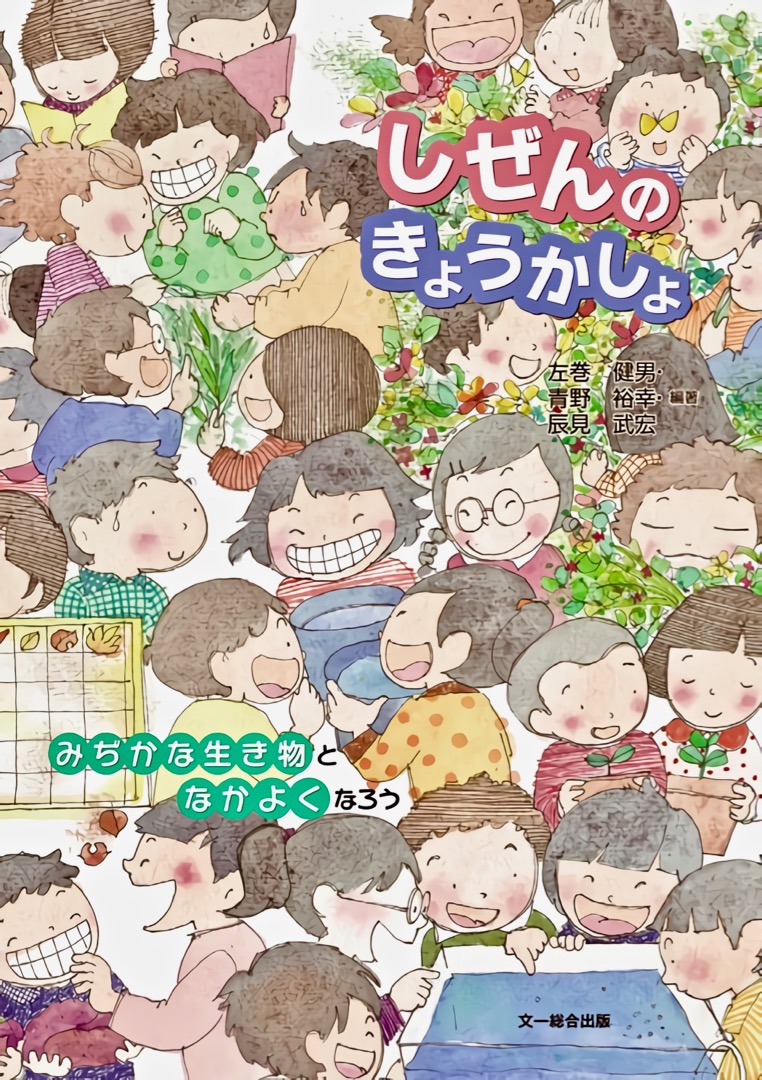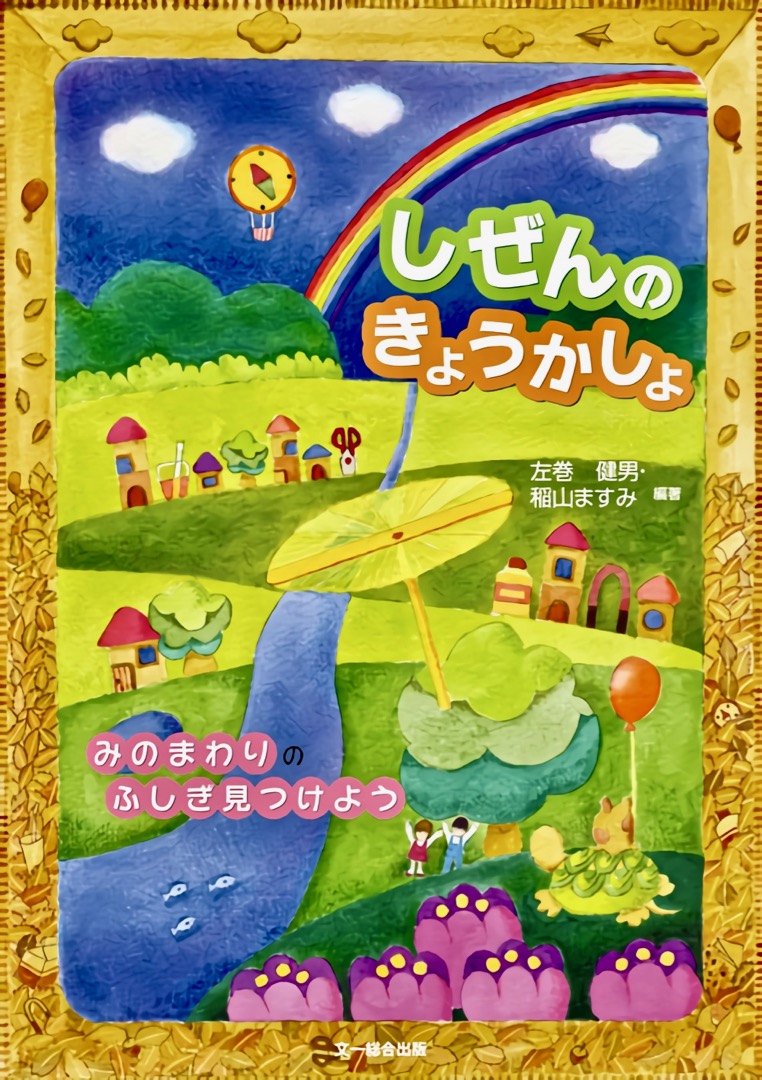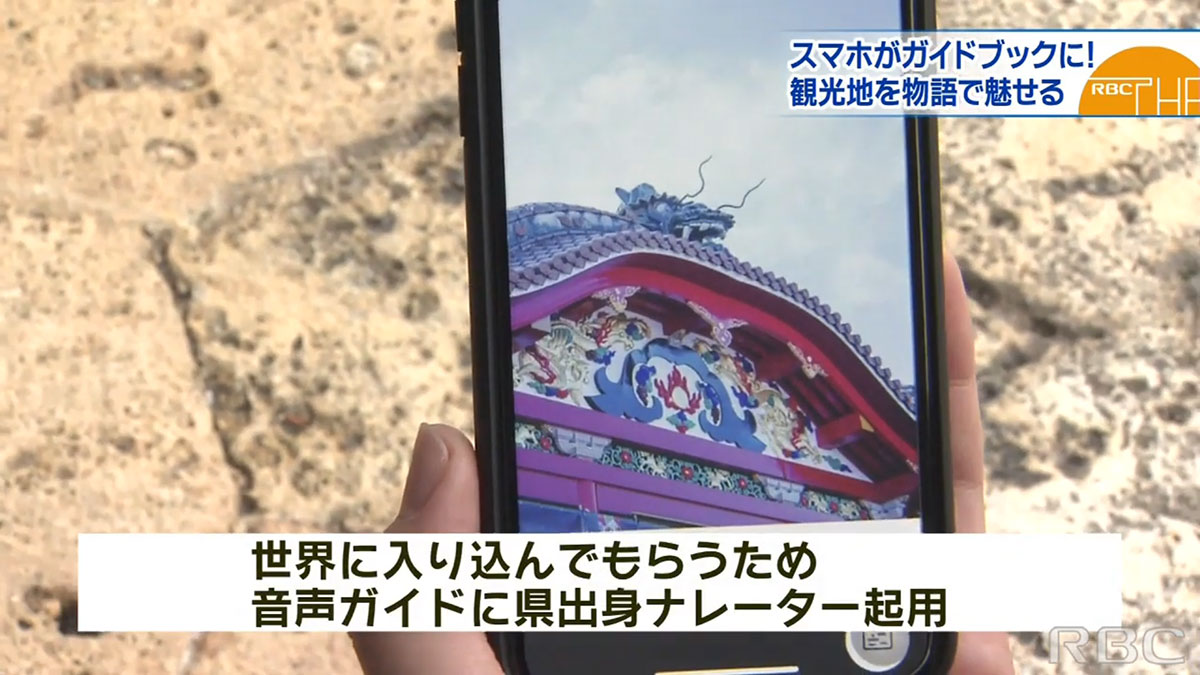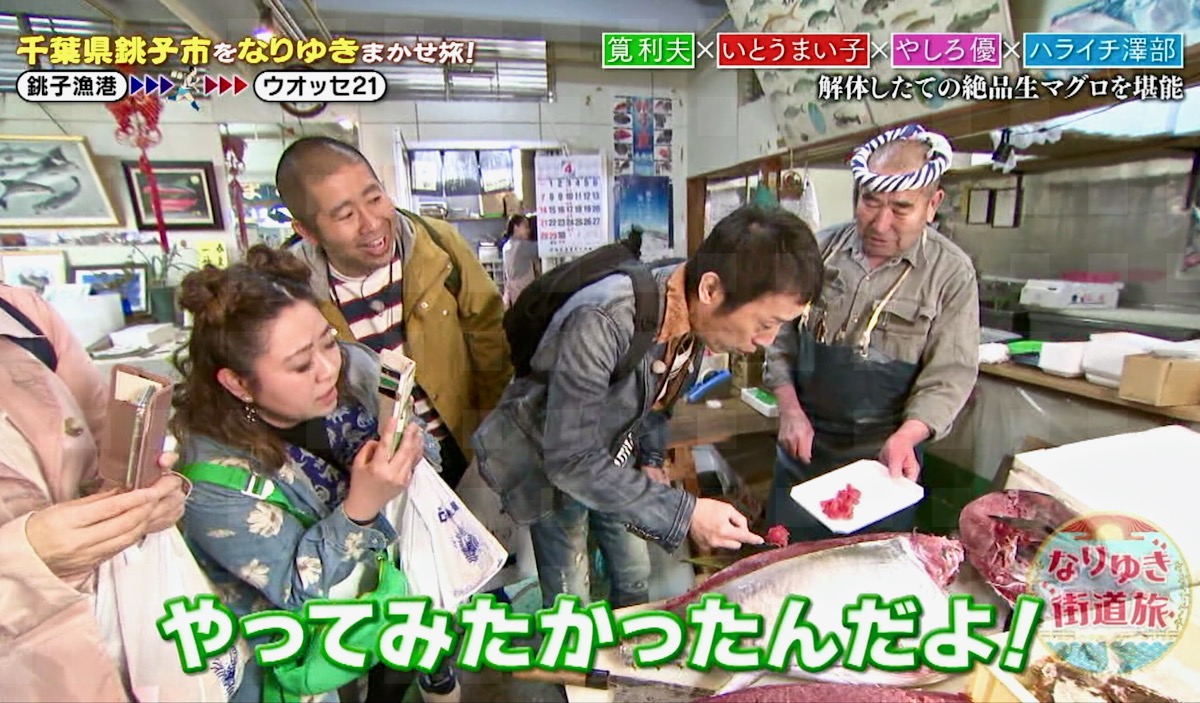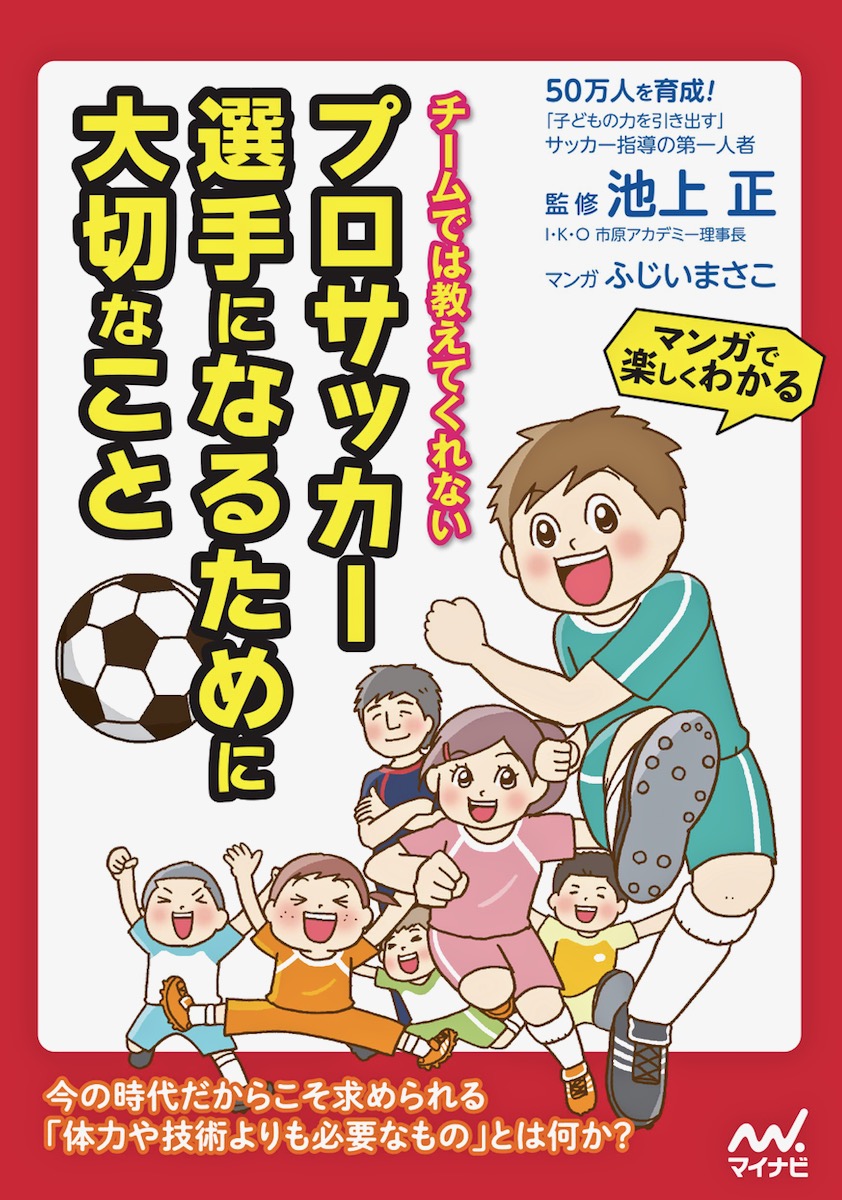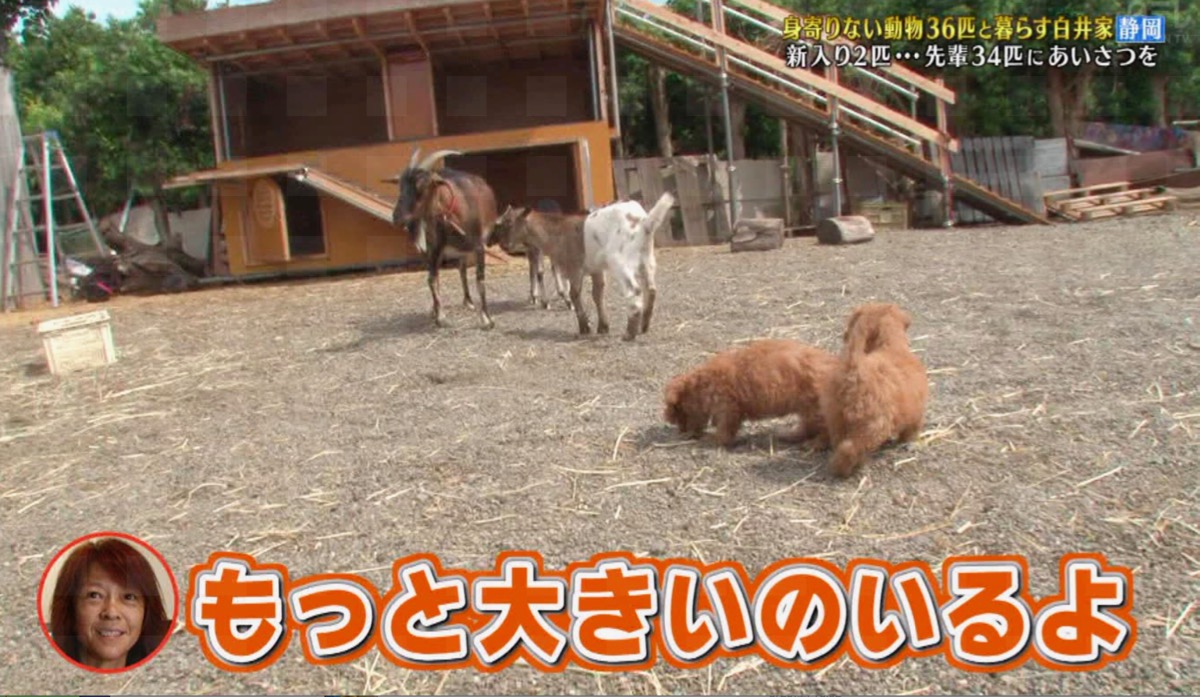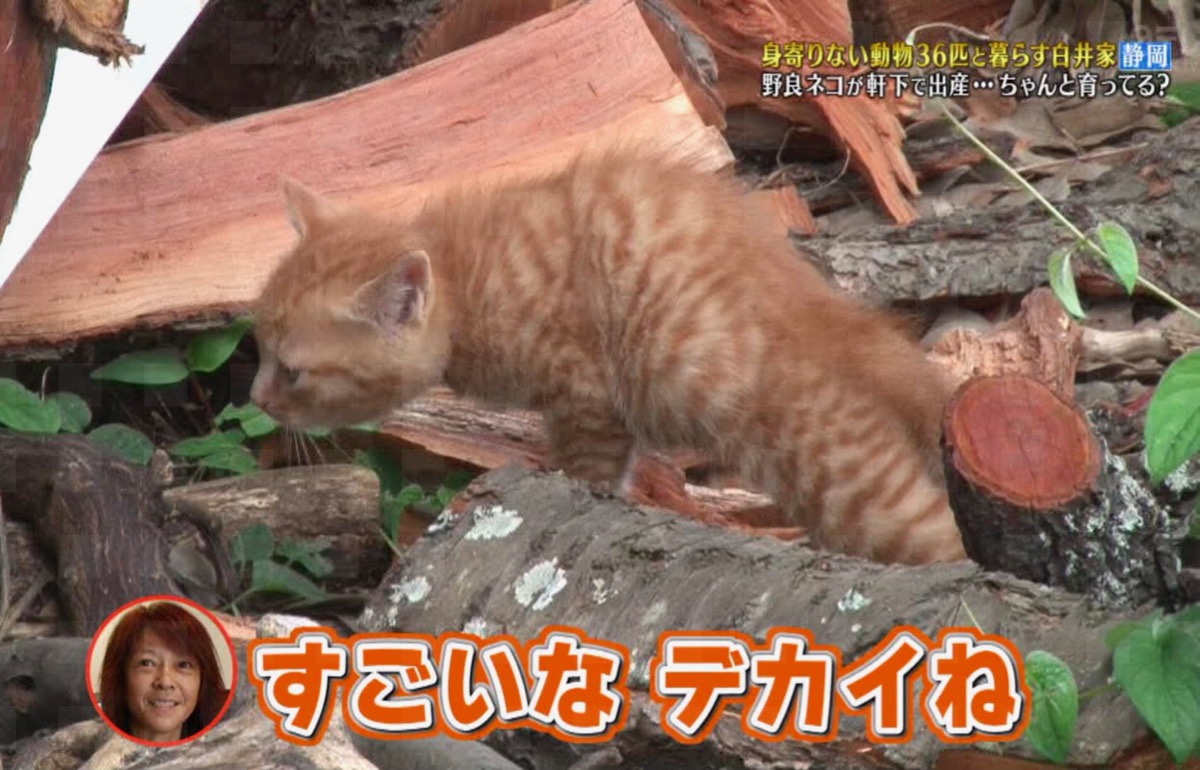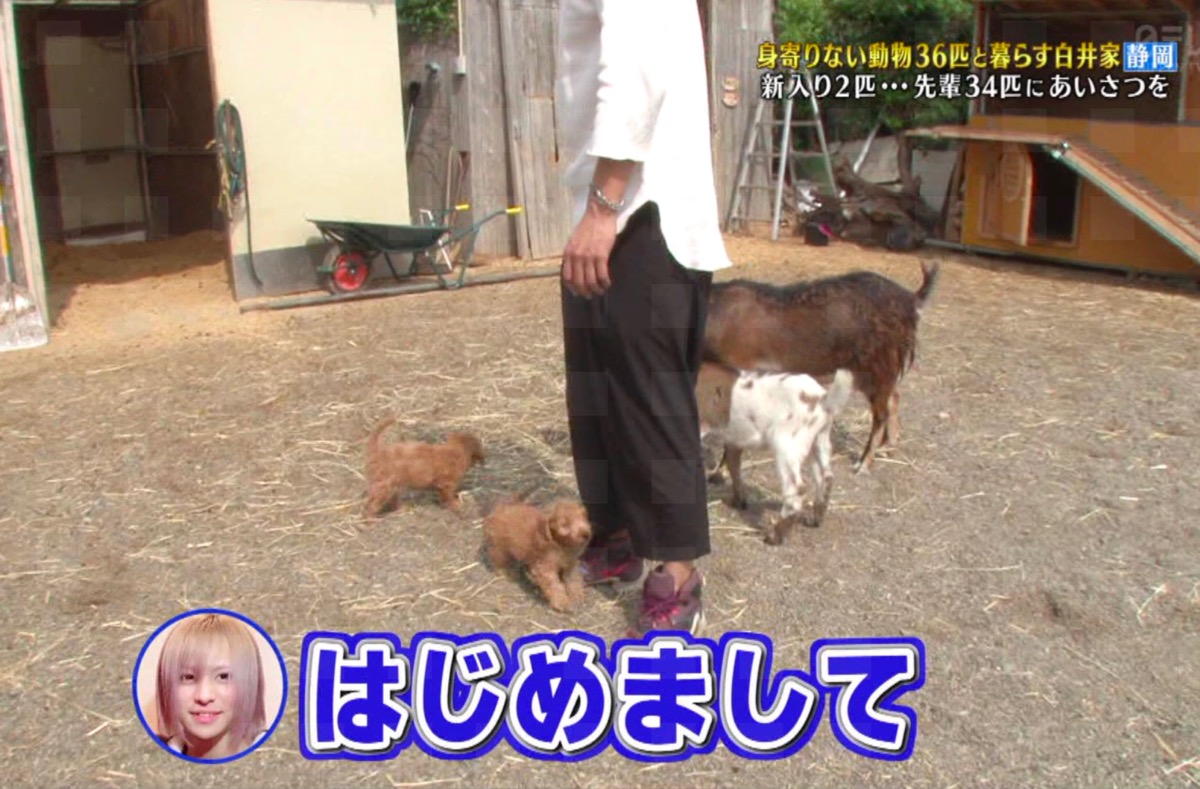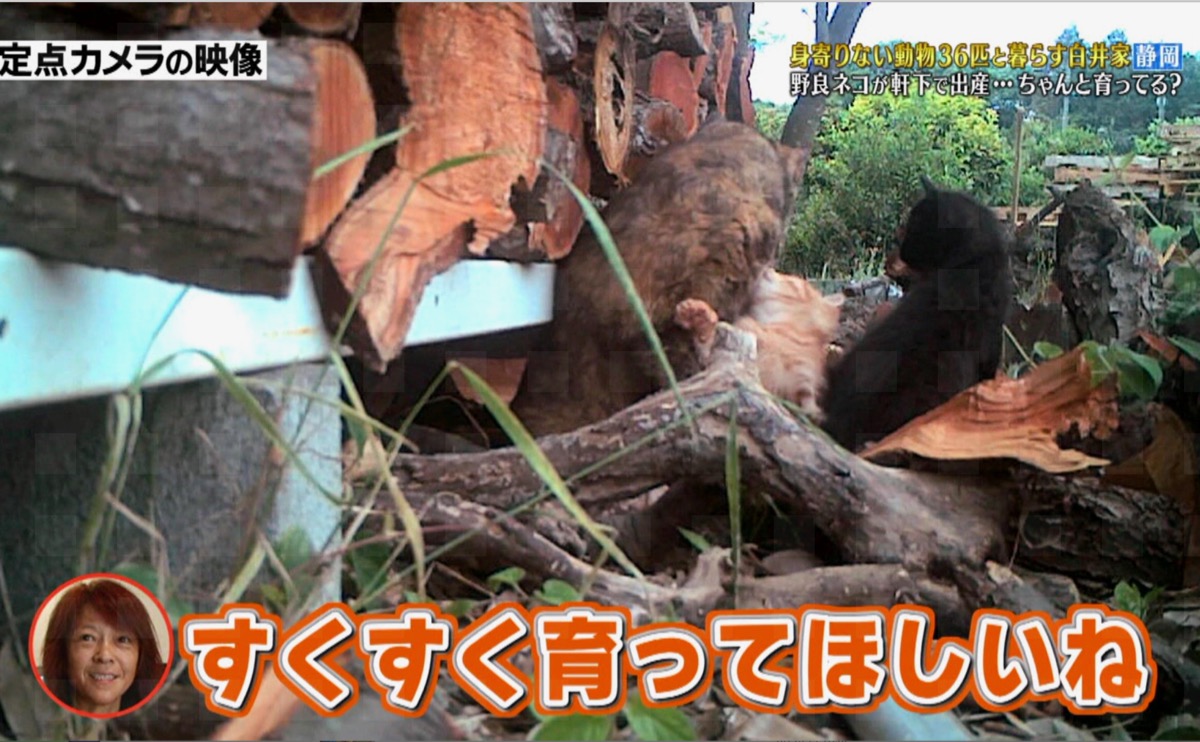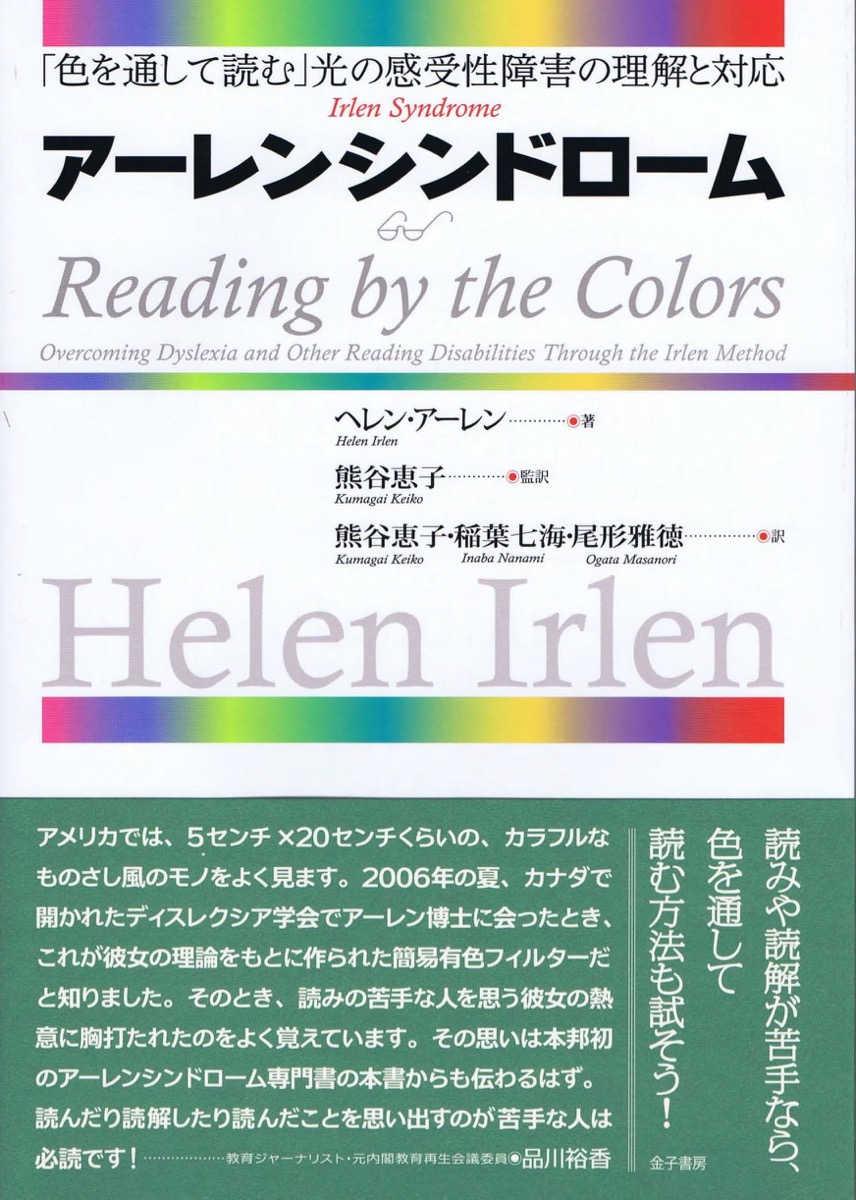
本の表紙 さとうゆたか
書名:におうのだあれ
著者:ジョナサン・ランバート、たにゆき
発行:大日本絵画巧芸美術
本の表紙 さとうゆたか
書名:はさみむし
(かがくのとも 2019年11月号)
著者:石森 愛彦
発行:福音館
本の表紙 さとうゆたか
書名:ごみしゅうしゅうしゃのゴンちゃん
著者:おおはし えみこ、田中 四郎
発行:チャイルド本社
商品名 さとうゆたか
商品名:ちゃんぽんうどんスープ
製造元:ヒガシマル醤油
わんぱくを丸ゴシック化 さとうゆたか
かな書体「わんぱく」を丸ゴシック化した「わんぱく丸」を作りました。
丸ゴシック「レラ」と組み合わせて総合フォントにします。
これが本日頒布開始した、レラと組み合わせた「わんぱくレラ」です。
テレビ番組 さとうゆたか
なんの番組か、ちょっと判らない…。
本の表紙 さとうゆたか
書名:トッカン 徴収ロワイヤル
著者:高殿 円
発行:早川書房
本の表紙 さとうゆたか
書名:僕たちは、宇宙のことぜんぜんわからない
著者:ジョージ・チャム、ダニエル・ホワイトソン
発行:ダイヤモンド社
本の表紙 さとうゆたか
書名:数字でわかる!からだのびっくり図鑑
著者:藤本幸弘、造事務所
発行:実務教育出版